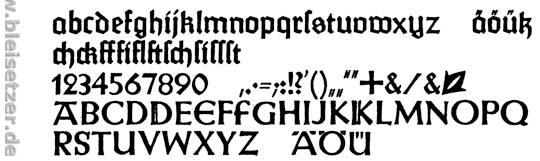
Fette Fraktur - Restaurantflyer ?
Der "Standard" ist doch "Zur Post" mit rundem s. Gibt's hier im Münchner Umland zu Hunderten. Wenn dann noch "Gasthaus" davor steht, ist immer hin wenigstens eins von drei s richtig ...
Übrigens: Es sind ja nicht nur die Leser, die mit Farktur nicht umzugehen wissen. Bei oder in Wurzen passiert man einen verfallenen Gasthof, der an der Façade mit der Frakturschrift »Zux Waage« wirbt. Habe leider jetzt kein Photo davon auf meiner Festplatte gefunden.
Manchmal ist es besser man fragt nach! Hattest Du beim vorbeifahren auch genügend Zeit um genau hinzusehen, handelt es sich wirklich um ein X, und nicht um ein rundes R ?
Da gibt es nichts mehr nachzufragen. Das Haus ist ruiniert. Vielleicht war ja die Küche wie die Beschriftung… Jedenfalls kehre ich in solchen Häusern möglichst nicht ein, weil genau dies meine Befürchtung ist. Wer ein Schluß-s in Gasthof akzeptiert, hat wahrscheinlich auch kein Problem mit Küchenschaben.
Jedenfalls steht dort wirklich:
Ich bin schon mehrmals dort vorbeigefahren und fahre extra jedesmal langsam, weil ich es nicht fassen kann. Wahrscheinlich hat man den unteren Haken für ein Ornament am r gehalten.
Manchmal ist es besser man fragt nach! Hattest Du beim vorbeifahren auch genügend Zeit um genau hinzusehen, handelt es sich wirklich um ein X, und nicht um ein rundes R ?
Aber das wäre nach dem u doch auch falsch! Und mal ehrlich, welcher Schildermaler kennt das runde r?
Die Verwechselung von x und r hatten wir hier im Forum auch schon mal (Leider weiß ich im Moment nicht mehr genau wo) Es gab da nämlich einen Laden für Damen und Hexxen-Mode.
Es ist unglaublich! Ich dachte, ich hätte da mal einen ganz originären Fehler aufgetan, aber der Wahnsinn scheint ja Methode zu haben. Jetzt stellt sich mir die Frage: Wie kann es eigentlich zu so einem Fehler kommen? In meinem Beispiel waren das Holzbuchstaben. Da vermute ich mal, daß der Schreiner, der die ausgesägt hat, ein Schriftmusterblatt hatte, und dann hat er sich halt das »schönere r mit dem Extraschnörkel« herausgesucht und der Kneiper hats ihm abgekauft. Aber der Hexxenfriseur: Stinknormale Folieschrift, am Rechner gesetzt – da muß man doch nicht nur keine Ahnung haben, sondern auch noch die x-Taste drücken, die ja nun mit an Sicherheit grenzender Wahrscheinlichkeit nicht in Fraktur, sondern in Grotesk beschriftet ist. Wie kann das passieren?
Es ist unglaublich! Ich dachte, ich hätte da mal einen ganz originären Fehler aufgetan, aber der Wahnsinn scheint ja Methode zu haben.
Aber der Hexxenfriseur: Stinknormale Folieschrift, am Rechner gesetzt – da muß man doch nicht nur keine Ahnung haben, sondern auch noch die x-Taste drücken, die ja nun mit an Sicherheit grenzender Wahrscheinlichkeit nicht in Fraktur, sondern in Grotesk beschriftet ist. Wie kann das passieren?
Wohl aus dem selben Grund weshalb manche anstatt dem langen-S das schluß-S setzen, sie gehen davon aus, der Lesende sei dumm und man müsse ihm daher entgegenkommen (Bevormundung).
Das verstehe ich nicht. Das x für r ist doch kein Entgegenkommen dem Leser gegenüber (weil er das ſ nicht kennt); es ist schlicht und einfach falsch.
Wie es zur Verwechselung kommen kann ist mir nicht erfindlich. Ich vermute aber, daß die Schrift nicht am Computer gesetzt wurde sondern irgendwie doch per Hand. Oder der Entwerfer hat sich den gesamten Buchstabenbestand angeschaut und das „wunderbar verzierte r“ entdeckt.
Irgendwo ist es doch nur logisch, wenn Deutsche von Heute z.B. das Lang-s als Gemeines-l interpretieren. Man kann doch nicht ignorieren, daß die Zeit, in der das Lang-s verwendet wurde, mindestens 60 Jahre her ist.
Und so kommt es dann halt bei der Interpretation alter Bücher zu solchen Beschreibungen wie:
"Papier: Zerkall-Bütten der Papierfabrik Zerkall Renker & Söhne, Zerkall über Düren
Jellenschrift der Schriftgießerei Gebr. Klingspor, Offenbach a.M."
Sich als Typograph heute darüber aufzuregen, ist eher snobistisch.
Da bin ich doch gern mal ein Snob.
Aber jetzt irritierst Du mich:
Irgendwo ist es doch nur logisch, wenn Deutsche von Heute z.B. das Lang-s als Gemeines-l interpretieren.…Und so kommt es dann halt bei der Interpretation alter Bücher zu solchen Beschreibungen wie:
"Papier: Zerkall-Bütten der Papierfabrik Zerkall Renker & Söhne, Zerkall über Düren…
Was stimmt daran nicht? Die Papierfabrik bezeichnet sich doch selbst so: http://www.zerkall.de/Deutsch/Index.Deutsch.html
Ich habe das Zerkall-Logo noch nie in gebrochener Schrift gesehen, aber in Antiqua sieht das Wasserzeichen so aus:
Es ging ja doch wohl mehr um die »Jessen«-Schrift …
Passt irgendwie hier her. Das ist mir neulich aufgefallen. Die Brauerei
meinte wohl, der Namenszug sei nicht mehr angesagt und hat ihn einfach
einer kleinen Schönheits-OP unterzogen. :wink:
vorher:
nacher: